一度は見学したい、印刷博物館。印刷の歴史を知ると文字が身近になり楽しくなる。
FONTPLUSでご利用いただけるフォントメーカー14社(2022年3月現在)をご紹介する連載。今回は「凸版印刷」です。
凸版印刷と言えば、世界最大規模の総合印刷会社です。1900年の創業以来、「印刷テクノロジー」をベースに社会的価値創造企業を標榜し、さまざまな事業展開を行っている会社です。最近では「すべてを突破する会社」というテレビCMのフレーズが最初に頭に浮かんできます。
さて、直近3回のFONTPLUSブログでは「イワタ」「大日本印刷」「モトヤ」を取り上げました。「イワタ」と「モトヤ」は、書体を設計開発し、印刷会社等へ活版印刷用の金属活字を納品していました。この2社は活字やフォントを製造販売する事業が会社の中核ですので、フォントメーカーと呼ばれています。
一方、前々回取り上げた「大日本印刷」と、今回取り上げる「凸版印刷」はフォントメーカーではなく、印刷会社です。ですが、この2社はフォントメーカー的な役割も果しているのです。
凸版印刷は、なぜ、フォントメーカー的な役割も果しているのか
現在ではデジタルフォントとコンピュータとプリンタがあれば、印刷物を制作することができます。しかしながら、この100年の印刷の歴史をさかのぼってみると、金属活字を使用して活版印刷した時代、写真技術を応用し写植機(手動写植機や電算写植機)を使用して印刷した時代を経て、今日のようなDTP(Desktop publishing)に代表されるコンピュータを活用して印刷するデジタル時代へと変化してきました。
先述のとおり、1960年代までは(それ以降も活版印刷は使用されるが)、凸版印刷の工場では、書籍、文庫本、週刊誌、教科書、漫画等のあらゆる印刷物が金属活字で活版印刷されていた時代がありました。見出し文字には大きな金属活字(初号、二号……)が使われ、本文には8、9、10ptなどの活字が使用されていました。金属活字なので、文字の大きさ毎、そして明朝体とゴシック体毎に鋳造する必要がありました。
つまり、印刷工場では金属活字が大量に必要だったのです。そんな中、印刷最大手である凸版印刷において、独自書体が誕生することは必然だったと思います。それが「凸版書体」です。活字があっての印刷なので、大きな印刷会社、新聞社、出版社等で自社のオリジナルフォントが誕生することは珍しいことではありませんでした。
印刷会社でありながらフォントメーカーの役割も果たしているのは、活版印刷が全盛だった時代に理由があったのです。
印刷や活字の歴史が一望できる「印刷博物館」、ご存知ですか?
凸版印刷本社であるトッパン小石川本社ビルに「印刷博物館」があるのはご存知ですか?
印刷博物館は、2000年に創設され、印刷や活字にまつわる常設展示やさまざまな企画展示が行われてきました。ここに来ると、印刷や活字の歴史を見て知って学ぶことができます。そして、印刷工房で活字を組む体験もできます。
人間文化において印刷が果たす役割は大きく、活字やフォントは人々がコミュニケーションする上ではなくてはならない存在です。それらが体系的に一望できる博物館としては日本最大級だと思います。海外では印刷や活字にまつわる博物館は数多く存在していますが、日本では多くないです。
漢字、ひらがな、カタカナ、アルファベットをすべて器用に駆使し、縦書きと横書きを併用する文化を持つのは日本語だけだと思います。世界と日本の歴史を見比べながら、印刷技術や活字の歴史を学ぶことは、とても重要であり楽しいことなのです。
ここで紹介する展示品は、印刷博物館のほんの一部にしか過ぎません。機会を作って、印刷博物館を訪問することをおすすめします。
百万塔陀羅尼
日本における印刷の歴史がいつから始まったのかご存知ですか。奈良時代に制作され、100万基の木製小塔に陀羅尼経を納められた「百万塔陀羅尼(ひゃくまんとう・だらに)」が日本の印刷の歴史のスタートと言われています。実はこの百万塔陀羅尼は、制作された年が明確である世界最古の現存印刷物でもあるのです。
グーテンベルク活版印刷
社会科の授業で「15世紀にグーテンベルクによって活版印刷が発明された」ということを学んだ人は多いと思います。では、その印刷技術はどんな意義があって、どのような歴史背景で誕生したかを知っている人はどれだけいるでしょうか?
印刷博物館に来ると、その理由や歴史背景を実際に目で見て理解することができると同時に、グーテンベルクの印刷術の発明がコミュケーションのあり方そのものを大きく変えたと感じることができます。それまでの書物は書写が中心だったので、一度に大量に制作することができず、1冊制作するのに数年かかる場合もありました。それが短期間で大量印刷できるようになったわけです。情報伝達のビッグバンと言ってもいいのではないでしょうか。
欧文書体の分類年表と欧文活字展示
凸版印刷では600書体以上の欧文活字(金属活字)を所有しているとお聞きしました。これだけ、数多くの欧文活字を所有している企業は少ないと思います。それら膨大な活字を現在も調査研究・分類し、データベース化をしているそうです。そのデータベースをみえる化した壮大な欧文書体の分類地図は一見の価値があります。また、代表的な欧文活字の展示(Bodoni、Baskerville、Garamond、Universなど)を見ることもできます。
ちなみに、印刷を版式で分類すると、凸版、凹版、平版、孔版と4つに分かれます。その中で一番歴史のある印刷方式「凸版」が会社名の一部になっているのは、感慨深いものがありました。
「凸版書体」の誕生
話題を凸版印刷の活字・フォントの歴史に戻しましょう。凸版書体の歴史をたどると、二瓶義三郎氏という方が重要人物のようです。
1933年(昭和8年)に二瓶氏(当時23歳)が東京築地活版製造所から凸版印刷に転職します。1937年(昭和12年)、凸版印刷は「ベントン彫刻機」を東京築地活版製造所から譲り受けます。当時、二瓶氏は彫刻種字(職人が手で金属活字を彫っていた時代があった)を正しくベントン母型に移植することに専念していました。1940年代に、小谷野禎興氏、山岡謹七氏、ミキイサム氏が凸版印刷に入社し、二瓶氏と一緒に凸版書体の制作に携わります。そして、1950年代後半には、8、9、10ポイントの凸版明朝が完成したと言われています。
凸版明朝は、誰でも読める、単純で美しい書体というのが最大の特徴と言えます。かなの「そ」「と」「や」「さ」「き」の筆の脈絡を省いた字形は、子供が間違って読んでしまわないようにという想いで制作していたものと思われます。戦前は行書体の脈絡を残す活字が中心であったが、凸版明朝の原字をみると、独特な雰囲気をもっています。
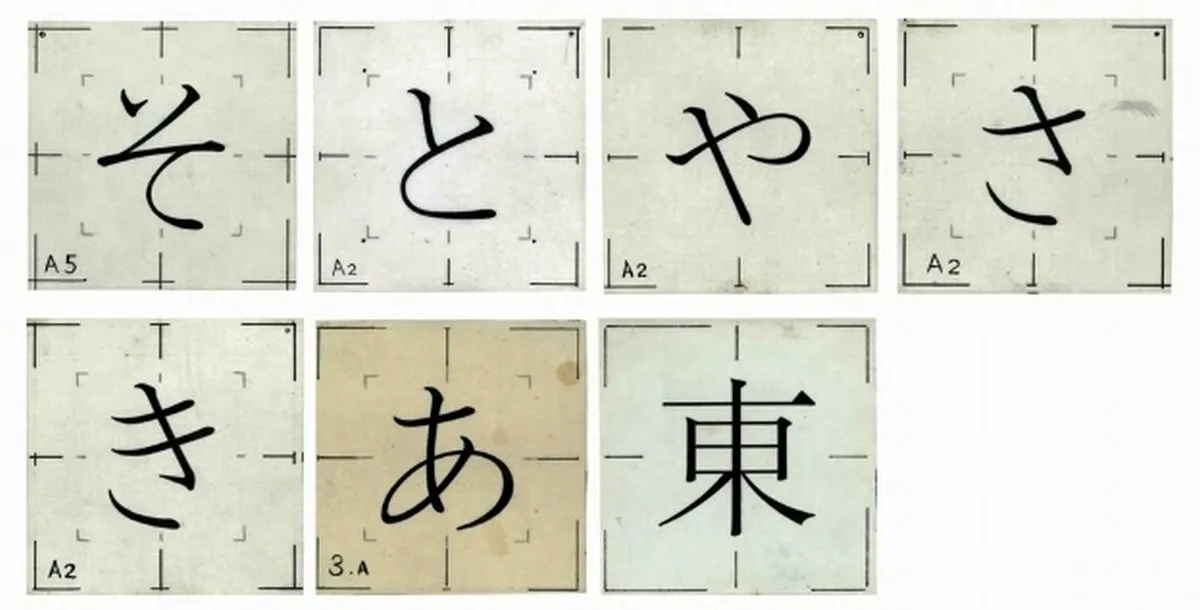
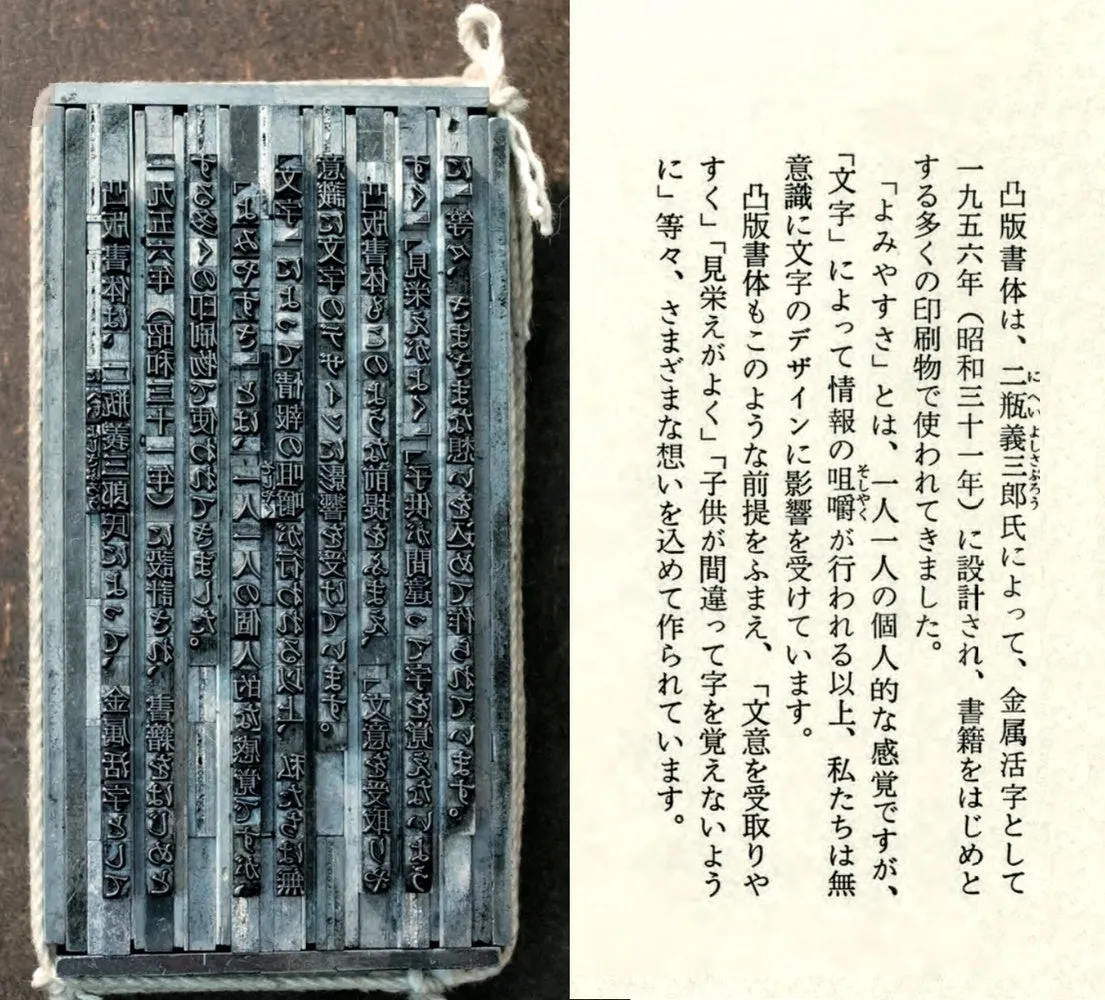
活字の歴史をざっくりと説明すると、「金属活字時代」「写植時代」「デジタル時代」の順で変遷していきます。そんな変遷の中で、凸版明朝の特徴である「そ」「さ」「き」等の筆の脈略が省かれた字形は、しっかりと引き継がれていくのです。
今の時代にマッチしたデジタルフォント「凸版文久体」の開発に着手
二瓶氏が中心となって制作した凸版書体が誕生してから、凸版印刷の工場では、出版社から依頼された書籍や雑誌は、凸版書体が使用されていたと言われています。当時、活版印刷された多くの市販書籍で凸版書体が使われていましたが、自社工場以外で、この活字が使われることはなかったようです。つまり、凸版書体は門外不出の書体だったのです。活版、写植から電子組版システムへ印刷の仕組みが変化する中、活字はアウトラインデータ化されました。凸版書体は、自社工場内で、脈々と引き継がれていたのです。
2010年、アップルからiPadが登場し、電子書籍等のデジタルコンテンツが本格的に普及しはじめました。凸版印刷で書体を担当する部門において「凸版書体は金属活字時代からデジタルフォント時代において市場ニーズに適した文字作りを行ってきたが、書体の文化性を考えれば、完成した書体であっても、今のデジタルコンテンツ時代にあった手直しが必要だ。企業マインドとしてのオリジナル書体を見つめ直そう」という熱い魂のようなものが動き出したとお聞きしました。
開発の方向性などの検討を重ねた後、凸版書体改刻チームが発足します。そして、2012年にフォントの試作に着手します。開発する書体のラインアップは本文用3書体(細明朝体、細ゴシック体、中ゴシック体)と見出し用2書体(太明朝体、太ゴシック体)の合計5書体でした。
本文用の明朝体は縦組みの可読性、本文用のゴシック体は横組みの可読性を第一に考えるコンセプトで開発をスタートさせます。なぜならば、ウェブのようなデジタル表現においては、横組みが圧倒的に多いからです。書体改刻チームは、横組みの日本語の文章をテンポよく読めて、内容が伝わりやすい書体は少ないと感じていました。そんな中、試作フォントを様々な世代の男女100名にアンケートを実施したところ、良好な反応が得られたとのことです。
凸版文久体のゴシック体の特徴として、ひらがな・カタカナの「でっぱり」が一般的なゴシック体とは逆になっています。「えっ、そうなの?」と思ったので、各社のゴシック体で「あさきゆめ」と組んでみたら、でっぱりが左についているのは凸版文久ゴシックだけでした。
また、凸版文久体の記号の雪マーク、雨マーク、曇りマークなどが、とても可愛らしいのです。「文字に萌える」若者を中心に人気があります。
「凸版文久体」という書体名の由来
「文久体」という名前の由来ですが、「文字による言語コミュニケーションで永久に使われる書体を提供したい」という思いが込められているそうです。小学生が習うやさしい漢字であり、振り子のように左ハライと右ハライが交互に現れるリズミカルなカタチに面白さがあり、音として口に出せば、リズムや拍の心地よさがあります。50年先も100年先も人々の記憶に残るシンボリックな名前として考案されたとお聞きしました。
そして、親みやすいキャラクターの「ぶんきゅうくん」が、ここ6年間、ブランド訴求に大きく貢献していると感じます。このキャラクターの制作者は、僕も大好きな祖父江慎さんです。頭が凸版印刷の「凸」のカタチになっていて、脚は常にクロスしていて「文」のポーズになっています。素敵ですね。
「凸版文久体」ファミリー5書体、2016年に完成
約60年前、金属活字としての凸版書体が誕生し、文庫本などで誰もが目にしている有名な書体ですが、凸版文久体ファミリー5書体が揃ったのは2016年6月。門外不出だった凸版書体が、デジタルフォントとしてオープン化された(誰もが購入してDTPやウェブで使用可能になった)のは、つい最近のことです。
凸版文久体は、macOS 10.12 Sierraからシステムフォントとして、「凸版文久ゴシック レギュラー」「凸版文久ゴシック デミボールド」「凸版文久見出しゴシック エクストラボールド」「凸版文久明朝 レギュラー」「凸版文久見出し明朝 エクストラボールド」が利用できるようになりました。
そして、2016年8月、FONTPLUSからWebフォントとして、凸版文久体ファミリー5書体が利用できるようになりました。